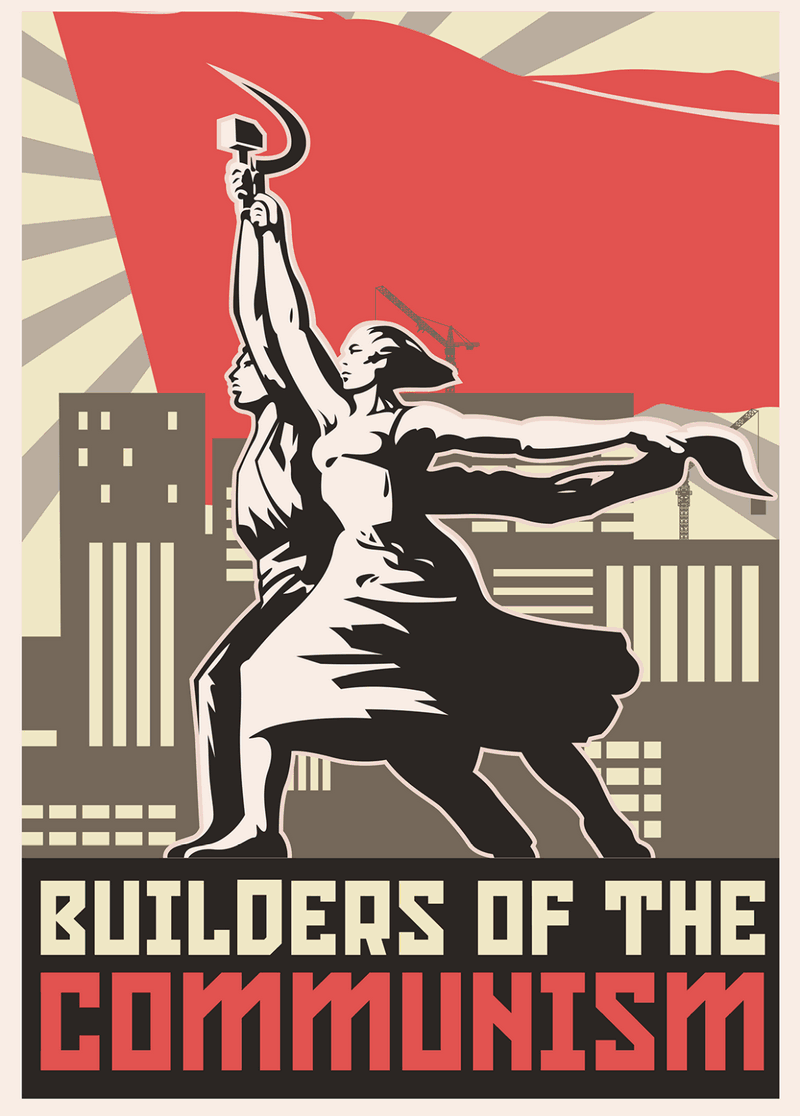
скачать Бесплатный шрифт Konstruktor (кириллица-латиница) От ANT на Пятница, 27 декабря, 2019 1 499 Konstruktor — это конструктивистский шрифт, созданный Иваном Филиповым. Основан на его шрифте Red October. Скачать Konstruktor font Скачать Red October font+ещё 2 шрифта Download Fonts Предыдущая новость Следующая новость Другие новости Web-Design полезности скачать A Note font (латиница) Web-Design полезности скачать Шрифт Neue sovet (кириллица) полезности скачать Текстуры салютов